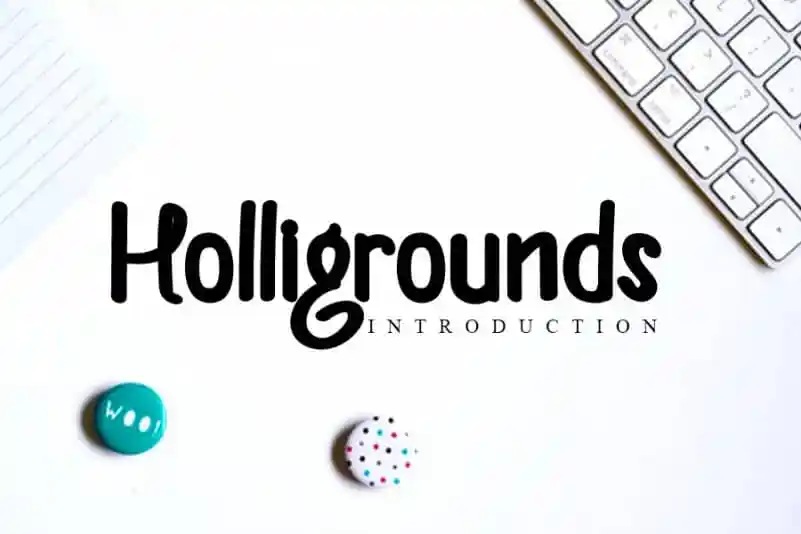
Helligrounds Display Font – Download Grátis
A Helligrounds Display Font é uma escolha perfeita para quem deseja adicionar um toque elegante e atual a qualquer projeto visual. Inspirada nos belos traços do caligrafismo, essa fonte mantém seus elementos clássicos ao mesmo tempo em que se destaca como moderna e inovadora. Suas variações proporcionam uma versatilidade extremamente valiosa, tornando-a ideal tanto para aplicações como cartões de visita ou títulos, quanto para criações de material de escritório. Seja você um designer gráfico profissional ou amador, a Helligrounds Display Font certamente atende às necessidades de quem busca uma fonte moderna e sofisticada, que se adapta perfeitamente a múltiplas utilizações.